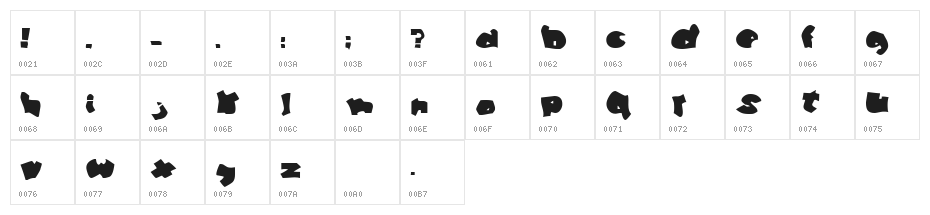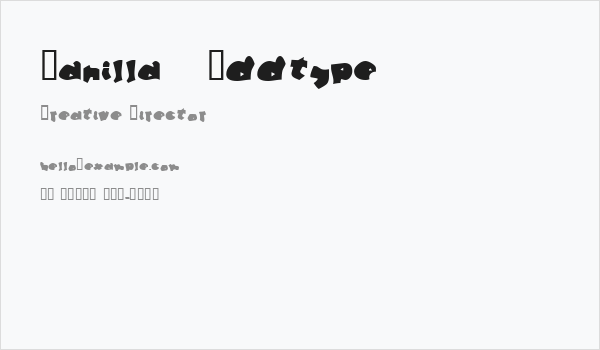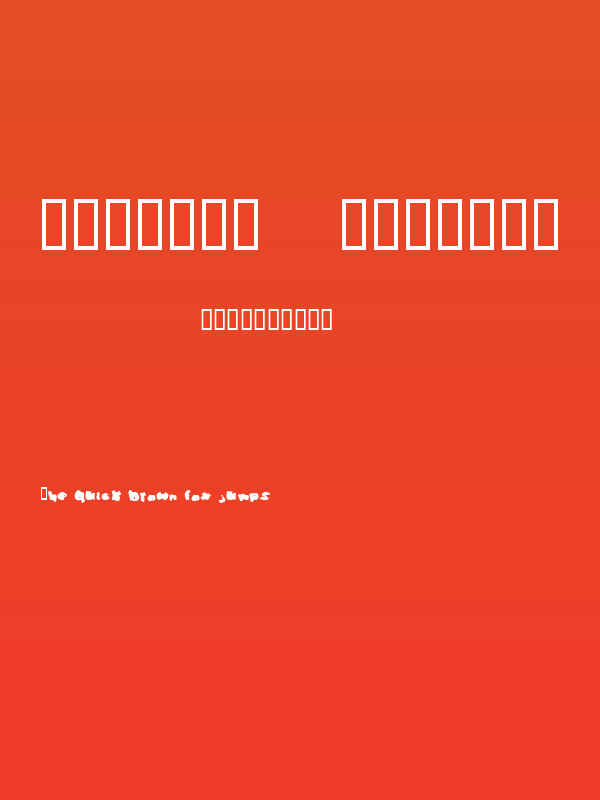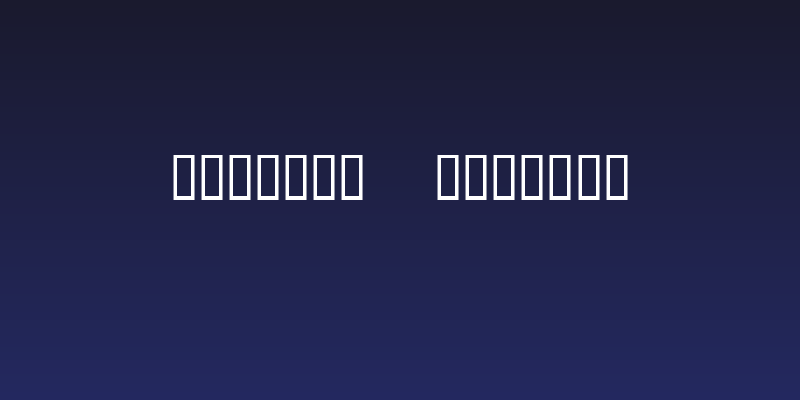
Manilla Oddtype Font
Acest font include 39 caractere. Clic pe orice caracter pentru detalii.
| Stil general | Whimsical, Artistic |
| Proiecte propuse | Artistic posters, unique branding, eye-catching headlines. |